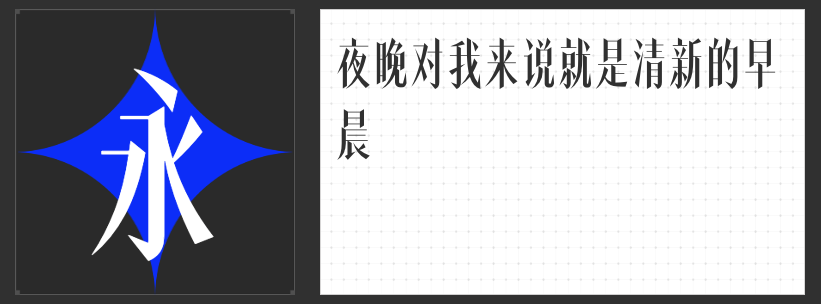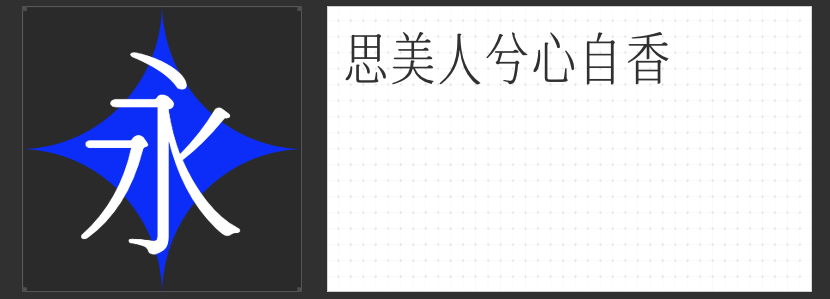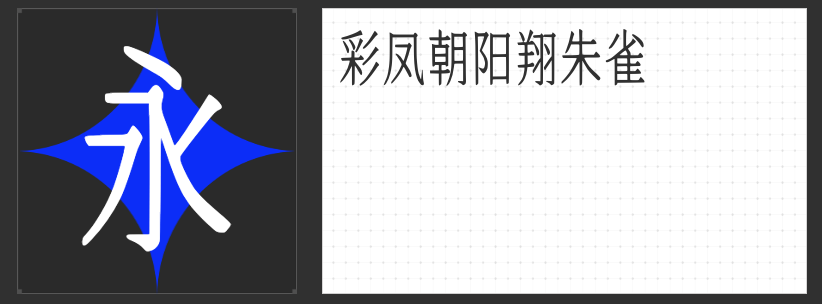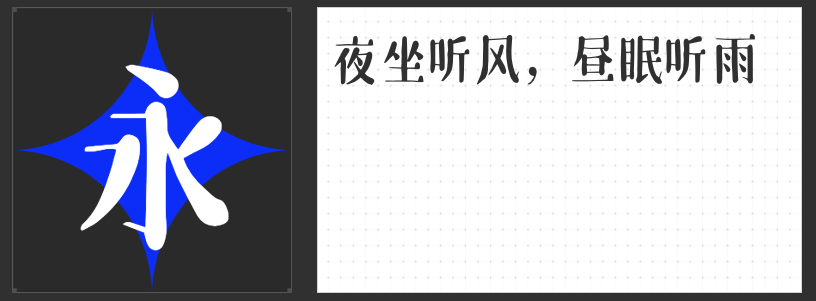
四款修长宋体推荐:设计中的优雅与科技交融之美
在字体设计的广阔天地中,宋体以其独特的韵味与历史底蕴,成为众多设计师的心头好。尤其是那些修长而不失风骨的宋体,更是为设计作品增添了几分雅致与灵动。今天,我们特别推荐四款各具特色的修长宋体字体,它们不仅继承了宋体的经典元素,更在细节处展现出非凡的创新与美感。
这款字体以手写感为基石,整体呈现出圆润而略显瘦长的形态。其笔画设计巧妙融合了传统宋体的横细竖粗特点,同时加入圆形元素装饰角,使得字体在保持古典韵味的同时,又多了几分趣味性与生动感。西文符号的设计同样圆润统一,与中文相得益彰,共同营造出和谐而富有活力的视觉效果。
二、高手兵克高雅宋
此款字体以瘦长为美,笔画转折处的尖角处理,赋予了字体一种难以言喻的优雅气质。竖笔画收笔处的向左切口,更是点睛之笔,使得整个字体在简洁中透露出不凡的品味。
三、机甲宋朱雀号
将宋体与机甲元素巧妙结合,这款字体在视觉上形成了强烈的冲击力。其笔画设计既遵循书法规范,又融入了机甲形象的硬朗与科技感,使得整个字型独特而富有未来感。
以简静优雅著称,这款宋体在原字形基础上稍作拉长,便展现出秀美修长的字型。其女性气质由内而外散发,如同一位温婉的美人,静静地诉说着宋体的悠久历史与文化底蕴。精致纤巧的衬线加入,更是为这款字体增添了几分细腻与柔美。
这四款修长宋体,每一款都蕴含着独特的设计理念与美学追求,无论是古典雅致还是现代科技,都能在设计作品中绽放出耀眼的光芒。